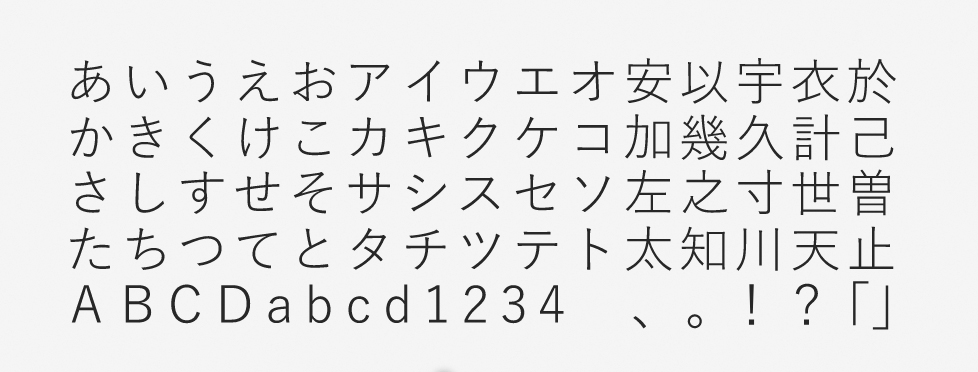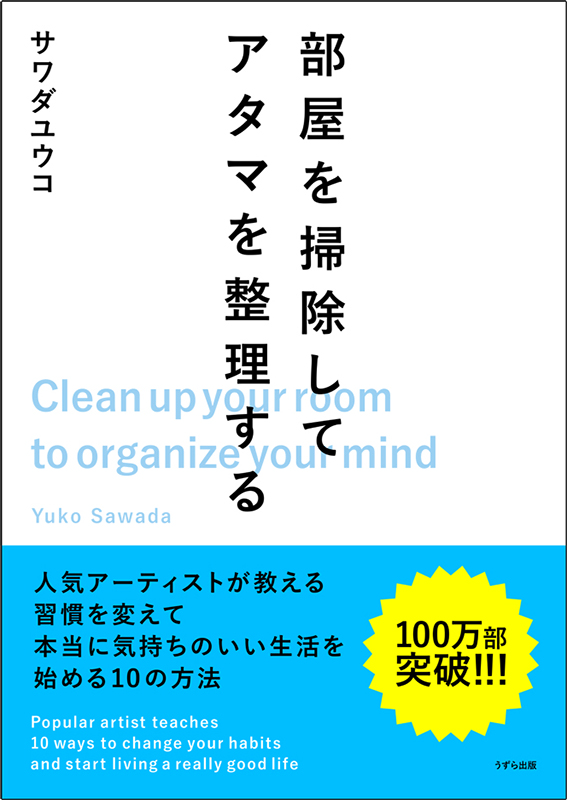
「游ゴシック体」について
游ゴシック体は字游工房による「游書体」シリーズの1つで、同社での販売は2008年に開始されました。 “普通のゴシック体” がコンセプトで、長文でも読みやすいスタンダードなフォントです。ひらがなのデザインについては、游明朝体と一緒に使うことを想定して開発されているため、ひらがなは游明朝の骨格を参照して開発されています。
「游ゴシック体」の特徴
游ゴシック体は、ゴシックMB101などと比べると字面が小さめです。テキストを組んだときに文字どうしの間にゆとりが生まれ、1文字ずつの識別性に優れた読みやすさが実現されます。漢字のふところはやや狭く、伝統的な文字の形へと近付けたデザインです。
游ゴシック体ファミリーは、7つのウエイトで構成されています。本文用の書体としてだけでなく、HやLなどのウエイトは見出しにも最適で、同じフォントで一貫性を保つことができます。
作例では書名をアケ組みにして游ゴシック体の持ち味を強調し、「整理整頓」されているような効果を出す工夫をしました。游ゴシック体は、級数を変え、色を変え、密度(文字間隔)を変えても全ての部分でバランス良くレイアウトできます。ストレスがなく読みやすい、今の時代に必須のフォントです。